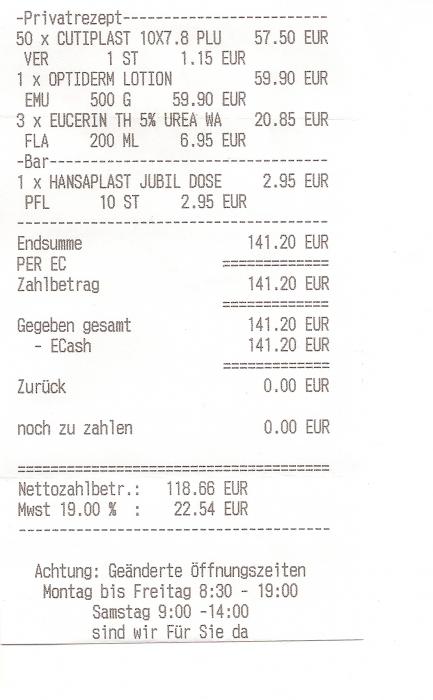
Quittung - Mischung Serif - Sansserif?
Was ist das für eine Schrift? Sie scheint eine Mischung von Serif und Sansserif zu sein.
Kassensystemhersteller haben ihre eigenen Schriften, die je nach eingesetzter Technik (Matrix, Thermo etc.) zum Einsatz kommt. Üblicherweise Fixweiten-Schriften und eben an die Ausgabetechnik angepasst, aber eben nicht als Truetype oder ähnlichem Format erhältlich. Aber ähnliche, wenn nicht gar fast identische, findest du, wenn du Ralfs Rat befolgst :-)